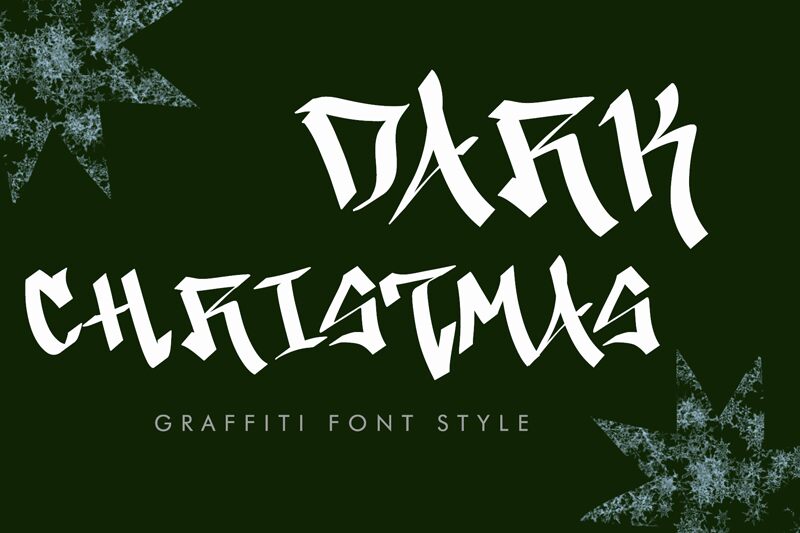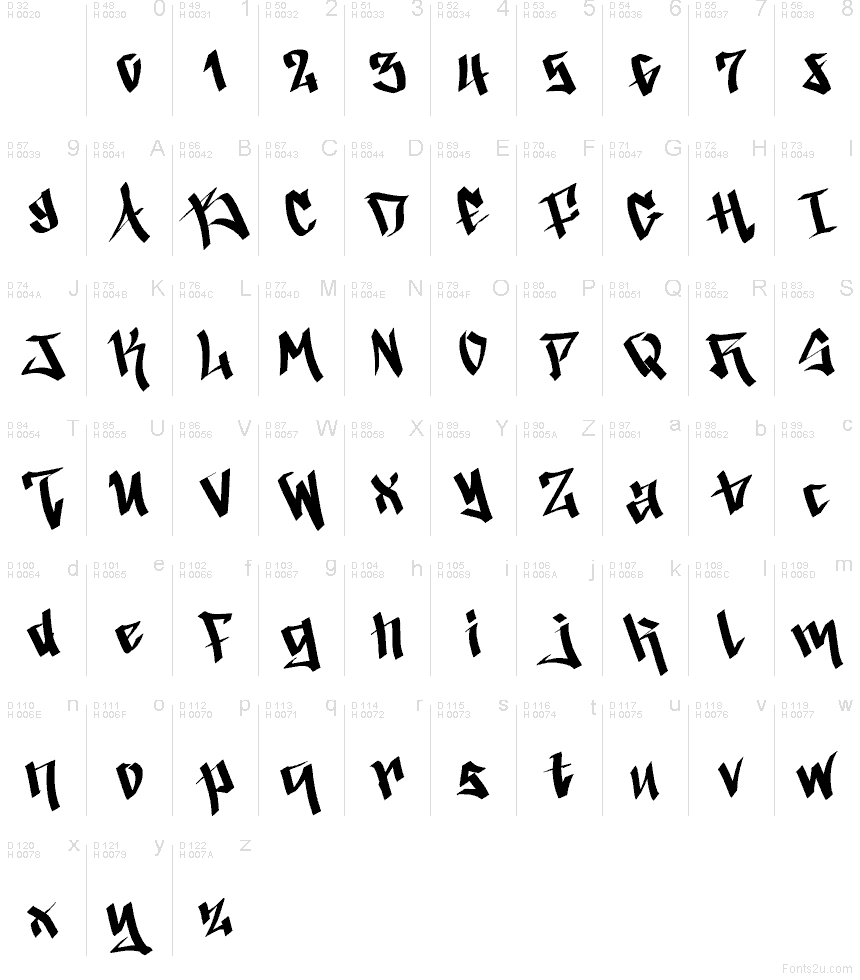
Dark Christmas to darmowy font w stylu graffiti, charakteryzujący się ostrymi, kanciastymi liniami i sznytem blackletter, co nadaje literom surowy, ręcznie wycinany rytm. Dzięki ostrym krawędziom, pochylonym kształtom i nieregularnemu przepływowi, krój ten kojarzy się bardziej ze sztuką uliczną niż z tradycyjnym świątecznym pismem.
Dark Christmas świetnie sprawdzi się w nagłówkach plakatów, ulotkach imprezowych, gadżetach okolicznościowych, oprawach muzycznych oraz grafikach świątecznych do mediów społecznościowych, gdzie poszukiwany jest bardziej zadziorny przekaz. Jego ostra, gotycka konstrukcja doskonale nadaje się do krótkich haseł, logotypów, bannerów eventowych i dekoracyjnych napisów, które mają wyróżniać się bez zbędnej delikatności czy tradycjonalizmu.